손으로 적시는 디자인 감성, 캘리그라퍼(Calligrapher).1
속도와 디지털로 대변되는 요즘 시대, 따라만 가기에도 숨이 찰 정도로 빠른 변화에 지친 사람들에게 아날로그적 감성이 다시금 고개를 들고 있다. 디지털이 가속화 될수록 이런 아날로그에 대한 욕구는 사회, 문화 전반적으로 점차 커지고 있고, 디자인 역시 그 흐름에 선구적으로 동참하고 있다. 특히 최근 그 흐름이 더욱 뚜렷하게 느껴지는 분야가 있는데, 바로 캘리그래피다. 모든 디자인의 기본요소라 할 수 있는 글자, 그것을 직접 손으로 그려내어 예술적 가치를 부여하는 캘리그래피는 그야 말로 사람들에게 가장 원초적인 아날로그 감성을 전달해주는 매개체이다. 여기에서는 손글씨로 사람의 마음을 움직이는 사람들, 캘리그래퍼의 이야기를 연재한다. 11문 11답의 형식으로 국내 캘리그래피를 이끌어가는 이들의 일과 고민, 그리고 그들의 생각을 엿보도록 한다. 그 첫 번째 시간으로 캘리그래피 작가 이상현, MBC미술센터의 박명호, 코루통디자인의 박효진을 먼저 만나보자.
Q1. 캘리그리피 전문가로써 자신의 첫 작품이 궁금합니다.
아마 2000년도로 기억하는데, 농심의 ‘春麵(춘면)’이 사람들에게 알려진 제 첫 작품입니다. ‘내 손에 쥔 붓 한 자루로 대한민국의 문화를 바꾸겠다’며 시작한 캘리그래피였지만 처음에는 인정받기 힘들었습니다. 그러다 TV, 신문, 잡지, 마트 등 여기저기서 제 작품이 선보여지니 너무도 흥분되었던 기억이 납니다.
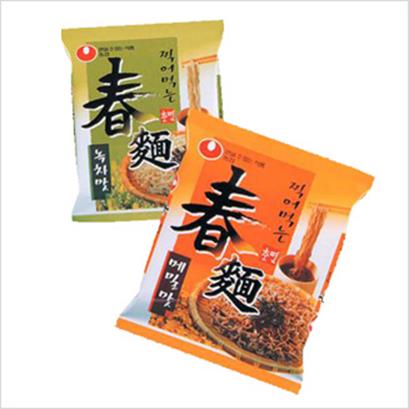
Q2. 지금까지 활동하면서 자신의 대표작 3점을 뽑는다면?
영화 『타짜』
제가 작업한 영화로고타이틀 중 대중들에게 가장 많이 알려진 작품일 것입니다. 실제 체험을 통해 로고를 작업하고 싶다는 생각에 화투패 내던지듯이 붓을 내리치며 글을 썼던 이야기가 있는 작업이죠.
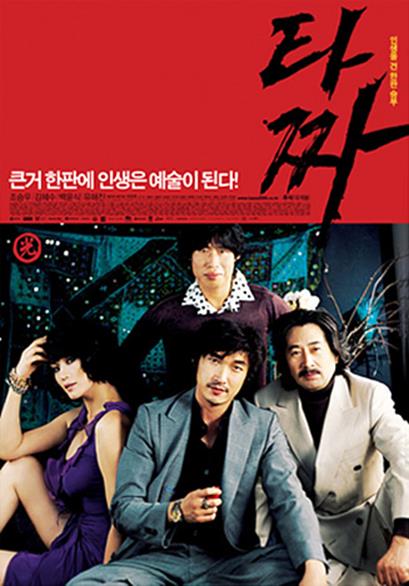
MBC수목미니시리즈「로열패밀리」
처음으로 작업한 드라마타이틀로고였습니다. 시나리오를 통해 많은 교감을 했고, 연습 없이 한번에 쓰여진 글씨가 선정된 경우였죠.
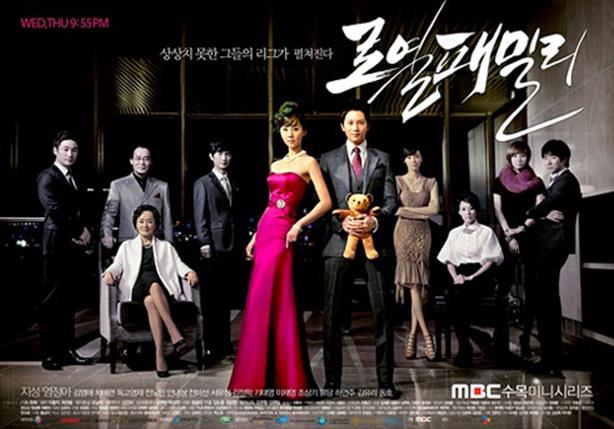
CJ패키지전용서체 「손맛체」
국내 최초의 패키지전용서체개발 작업입니다. 폰트를 만들기 위해 2,350글자의 원도를 약 3개월을 하루도 쉬지 않고 작업을 했었던 기억이 나네요. 어깨에 침을 맞아가며 작업에 몰두했던 잊지 못할 최고의 작업이었죠.
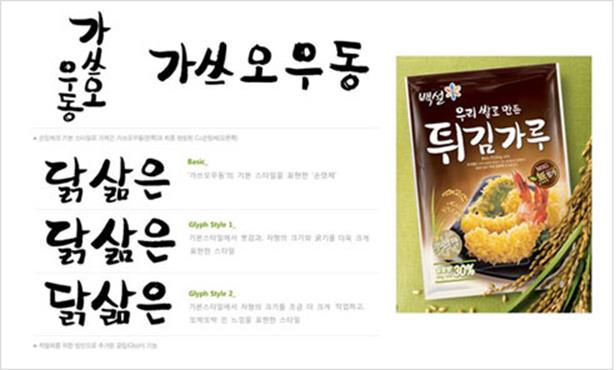
Q3. 일명 B컷이라 불리는 세상에 빛을 보지는 못했지만, 만족스러웠던 작업이 있다면?
조폭마누라3
영화의 이미지를 담아내기 위해 많은 고심을 거쳐 작품에 임했지만 안타깝게도 붓 맛이 살아 있는 캘리그래피가 선보여지지 못했습니다.
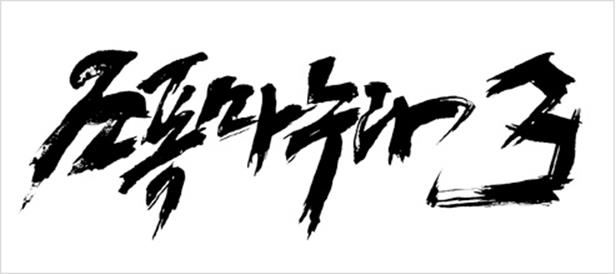
불꽃처럼 나비처럼
영화 ‘불꽃처럼 나비처럼’에서 영화 전반의 서화관련 자문을 맡은 적이 있었습니다. 천호진씨, 수애씨의 글과 그림을 그리는 교육 뿐 아니라 로고타이틀의 작업까지 맡았는데, 아쉽게도 로고타이틀은 사용되지 않았습니다.
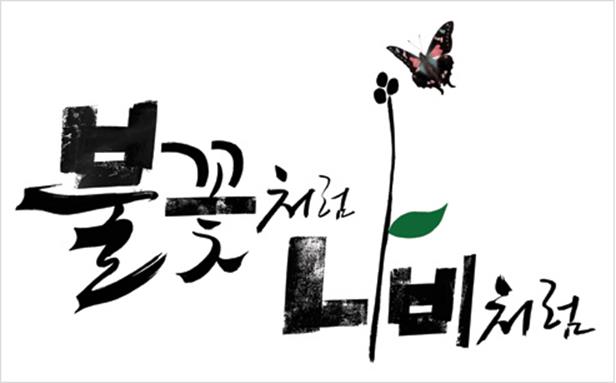
Q4. 캘리그래피에 느끼는 가장 큰 매력은?
묵향이라는 묘한 설레임과 항상 살아 움직이는 내 손을 볼 때 많은 생각을 합니다. 그리고 하루의 일과를 마치고 잠자리에 들 때 ‘오늘도 글씨 원 없이 썼다’라는 흐믓한 미소를 짓습니다. 내가 이렇게 작업을 하고 있다는 것은 언제나 나에게 새로운 도전의 기회가 있어서라고 생각합니다. 디자인이라는 큰 울타리 속에서 우리의 글이 새로운 생명력으로 꽃을 피울 수 있도록 늘 다양한 분야와 교감해야 할 기회를 만들고 도전한다는 것이지요. 그리고 무어보다도 제가 좋아하는 묵향을 항상 맡을 수 있다는 것이 저를 웃게 만드는 것 같습니다.
Q5. 캘리그래피는 한글과 밀접한 관계를 맺고 있습니다. 캘리그래피 관점에서 한글의 디자인적 매력은?
한글은 다른 문자와는 달리 글꼴의 구성 자체가 과학적이며, 조형적입니다. 그 조형에서 보여 지는 디자인적 요소는 매우 뛰어나다고 생각합니다. 또한 한글에서 나타나는 받침은 많은 조형적 변화를 만들어 냅니다. 그래서 받침이 있는 글자는 그 받침을 더욱 강조를 함으로써 문장에 리듬을 주기도 합니다. 획수가 많은 글자는 크게 표현하고 획수가 적은 글자는 작게 표현하기도 합니다. 이것이 캘리그래피에서 보여 지는 가장 큰 매력이 아닌가 싶습니다. 한가지를 더 말하자면 필기의 도구를 서양의 펜이 아닌 동양의 모필, 즉 붓을 이용한다면 문자의 강약을 통해 리듬을 표현하고 감성의 표정을 만들 수 있다는 것입니다.
Q6. 캘리그래피 시장이 커질수록 그에 따라 고민해야 할 문제점도 생길 것이라 생각합니다. 현재 캘리그래피 분야에 문제점이 있다면?
‘아름다운 글씨’라는 뜻으로 본다면 지금의 난무하는 수많은 손글씨들 역시 캘리그래피 작업이라고 볼 수 있을 것입니다. 여기서 중요한 것은 글씨를 진실되고 올바르게 써야한다는 것입니다. 단지 예쁜 글씨가 아니라 자신의 작업에 대해 진실이 담긴 이야기를 할 수 있어야 합니다. 또한 손글씨라고 정확한 메시지를 전달하는 가독성을 간과해서는 안됩니다. 글씨에 기분을 담아 흐름을 넣다 보면 틀린 오자를 범하기 쉬운데 그 점도 조심해야 되고요. 한글의 올바른 표정과 본질을 지켜야 합니다. 우리가 쓴 글씨로 모두를 행복하게 만들 수도 있지만 잘못된 글씨로 인해 우리의 문화를 망칠 수 도 있기 때문입니다. 예술은 그 시대의 문화를 만들고 예술가는 그 문화를 책임 질 수 있을 때 쓸 수 있는 말이 아닌가 싶습니다. 그러기 위해서 저도 작업을 하면서 많은 고민을 하고 있습니다.
Q7. CF, 출판, 영화, 방송 등 많은 분야에서 캘리그래피가 각광을 받고 있는데, 이외에도 캘리그래피가 접목될 만한 새로운 분야가 있다면?
미디어 아트의 분야도 있다고 봅니다. 정적인 평면작업에서 동적인 작업으로 살아 숨쉬는 한글의 이미지를 표현하는 것이죠. 한글의 자음과 모음, 그리고 아름다운 메시지를 전달하기 위한 텍스트의 작업에 보다 많은 이야기가 담길 수 있는 미디어작품이 앞으로 캘리그래피가 도전해야 할 장르가 아닌가 싶습니다.
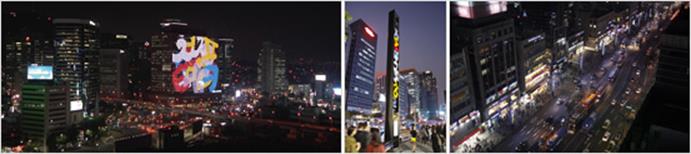
Q8. 글씨를 쓰는 데는 붓, 펜, 연필 등 다양한 도구가 사용됩니다. 개인적으로 선호하는 도구는 무엇인가요?
서예를 전공한 저는 그래픽적인 디지털 서체를 넘어 우리의 정서를 담아내는 글씨를 디자인에 소개하고자 캘리그라피라는 이름으로 지금까지 달려왔고, 처음의 마음이 그렇듯 지금도 붓과 먹, 그리고 화선지를 이용한 작업을 선호합니다. 예부터 붓이 귀할 때 붓 대용으로 대나무를 깎아 붓을 만들고 칡뿌리를 이용해 글을 쓰는 등 여러 도구를 이용해 글을 써왔었습니다. 더욱 좋은 감성을 표현하기 위해서 풀의 뿌리를 이용하여 글을 쓰기도 하지만 가장 어렵고도 가장 매력적인 도구는 붓(모필)인 것 같습니다.
Q9. 개인적인 취미, 혹은 재충전의 방법은?
많은 사람들과 이야기 하는 것을 좋아합니다. 어떠한 대상의 느낌을 글로 표현해야 하기에 혼자만의 생각으로는 가끔 작업의 한계를 느낄 수 밖에 없습니다. 그래서 다양한 직업을 갖은 분들과 술도 한잔하며 많은 만남의 자리를 하고 있습니다. 많은 대화를 통해 서로의 생각을 이해하고 교감하다 보면 언제나 그들은 저의 스승이 된답니다.
Q10. 캘리그래피를 배우려는 사람들에게 한마디.
캘리그라피는 문자를 다루는 일입니다. 문자를 기록한다는 것은 한 시대의 역사를 만들어가는 중요한 행위입니다. 그렇기에 붓을 든다는 것은 막중한 책임감이 있는 작업임을 알았으면 합니다. 누구나 가지고 있는 끼(감성)는 위대합니다. 하지만 자신에게 솔직하지 못하기에 표현을 못하는 것이지요. 붓은 용기 있는 사람만이 들 수 있다고 생각합니다. 조금 더 솔직하게 조금 더 용기를 내어 붓을 잡아 보세요. 세상이 아름다워 집니다.
Q11. ‘캘리그래피는 OOO다.’
캘리그라피는 마음을 담은 표정이 있는 글씨입니다. 그러기에 우리는 그 솔직함에 웃습니다.
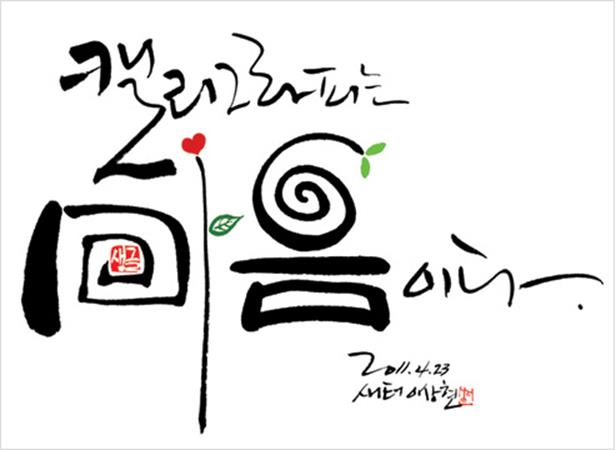
Q1. 캘리그리피 전문가로써 자신의 첫 작품이 궁금합니다.
저희 같은 경우는 처음부터 캘리그래피 작업을 하지는 않아요. 먼저 글꼴 디자인 위주로 작업을 하고 어느 정도 디자인적 시각을 키우고, 감각이 생기면 캘리그래피 작업을 하게 되죠. 방송에 있어 로고 타이틀은 상당히 중요한 부분인데, 캘리그래피로 제작하는 것에 무게를 더 두는 것이죠. 캘리그래피 스타일로 처음 작업한 것은 80년대 MBC 오락프로그램이었던 ‘화요일에 만나요’ 일겁니다. 오래 전이라 확실하게 기억이 나진 않지만. 지금의 캘리그래피와는 스타일이 많이 다르죠. 붓으로 작업한 후, 디자인적으로 약간 다듬어서 만든 로고타이틀입니다. 최근에는 아마존의 눈물이 좋은 반응을 받기도 했어요.
Q2. 지금까지 활동하면서 자신의 대표작 3점을 뽑는다면?
방송 로고 타이틀을 주로 작업하다보니, 아무래도 시청률이 좋게 나오는 프로그램이 기억에 많이 남습니다. 방송은 특성상 사람들의 반응을 쉽게 알 수 있어요. 인기 있는 프로그램은 많은 사람들에게 노출되게 되고, 자연스레 로고 타이틀도 기억에 남게 되는 것이죠. 그런 프로그램의 로고 타이틀 작업은 저에게도 많은 자부심을 주곤 합니다. 예를 들면 선덕여왕, 욕망의 불꽃, 신돈 등이 있겠네요.
Q3. 일명 B컷이라 불리는 세상에 빛을 보지는 못했지만, 만족스러웠던 작업이 있다면?
B컷 프로젝트라고 딱히 보여드릴 만한 것은 없습니다. 보통 로고 타이틀 작업은 연출진과 지속적인 의견교류를 통해 프로그램에 어울리는 것으로 결정하게 됩니다. 그렇기에 방송에서 보여지는 것이 가장 이상적인 상태라고 할 수 있죠. 크게 보면 연출진과 저희는 하나의 프로그램을 만드는 한 팀이라 볼 수 있으니, 여러 개의 시안 중 선택되지 않는 것은, 아쉽게 떨어졌다기 보다는 함께 진행하는 과정의 일부분이라고 생각합니다.
Q4. 캘리그래피에 느끼는 가장 큰 매력은?
Q10. 캘리그래피를 배우려는 사람들에게 한마디.
현재는 캘리그래피를 하시는 분들이 많이 계신 것 같습니다. 비슷한 느낌의 캘리그래피 작업들도 그만큼 많이 생겨나고 있고요.(한편으론 아쉽기도 합니다.) 그래서 캘리그래피에도 자신만의 스타일과 컨셉이 있다면 캘리그래퍼로써 더 전문적인 작업을 할 수 있지 않을까 하는 생각을 합니다. 자신의 글씨 스타일, 자신의 성향이나 관심사에 맞는 글씨들을 표현해가면 자연스럽게 스타일이 잡힐 거라 생각합니다.
Q11. ‘캘리그래피는 OOO다.’
‘캘리그래피는 슬로우디자인이다.’ 마음과 몸 모두가 급하지 않아야 좋은 글씨가 나오는 것 같습니다. 한 획 한 획 쓰면서 어떤 느낌을 주어야 할지 머릿속에서 상상하며 조심스레 그어가는 것. 바쁘고 복잡한 시대에 캘리그래피가 사랑을 받는 것은 조금 더 천천히 속도를 내며 가고픈 사람들의 마음을 움직일 수 있기 때문인 것 같습니다. 앞으로 제 글씨가 그런 역할을 하기 바라고 박효진의 캘리그래피는 그런 스타일을 가진 글씨로 발전 해 가길 희망합니다.